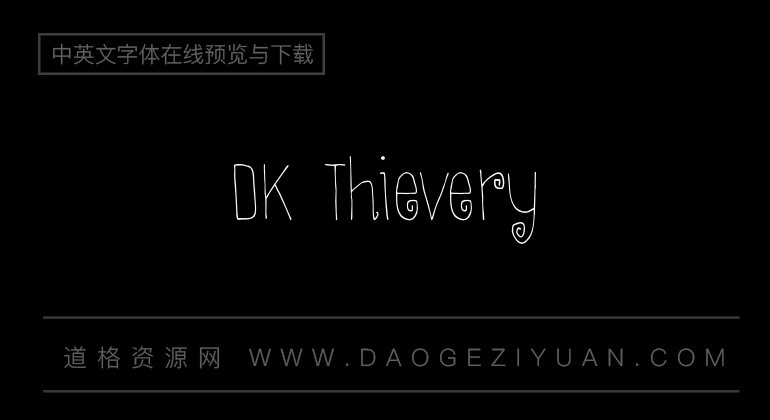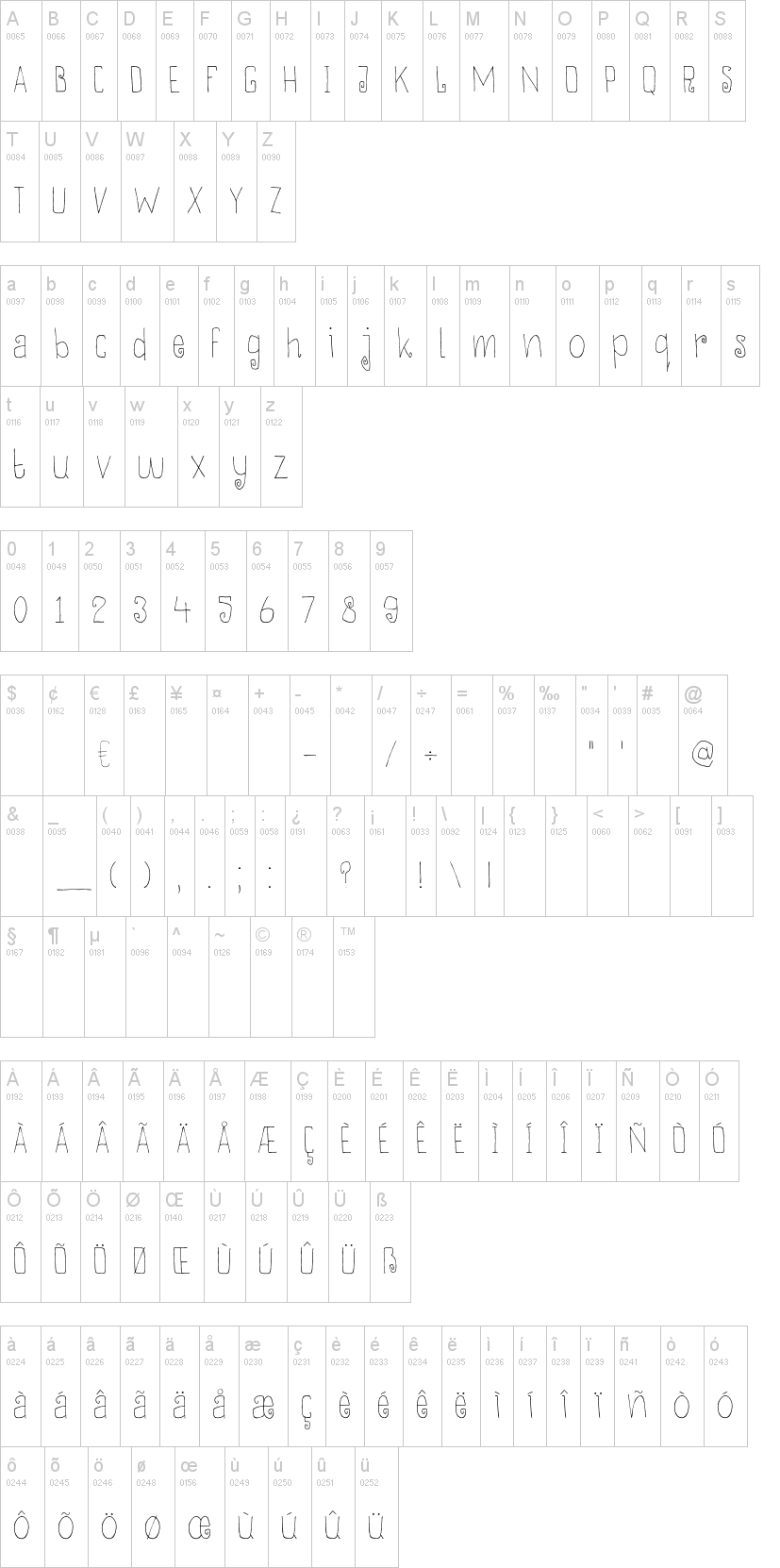
DK Thievery
? DK Thievery 是一款漂亮的手写字体,它拥有自然的曲线和流畅的笔触,可以用于各种印刷品,包括海报,书籍,杂志,婚礼邀请函,商业广告等。它的字形结构紧凑,可以提供出色的可读性,并且拥有大量的字符,可以满足多种语言的需求。它还拥有大量的斜体,可以添加更多的灵活性和个性化。
DK Thievery是一款非常不错的手写艺术字体,具有很好的视觉感,适合于文化类的宣传设计、商业类品牌的广告和产品包装设计以及个性化文字排版等较多场景。
DK Thievery字符映射图